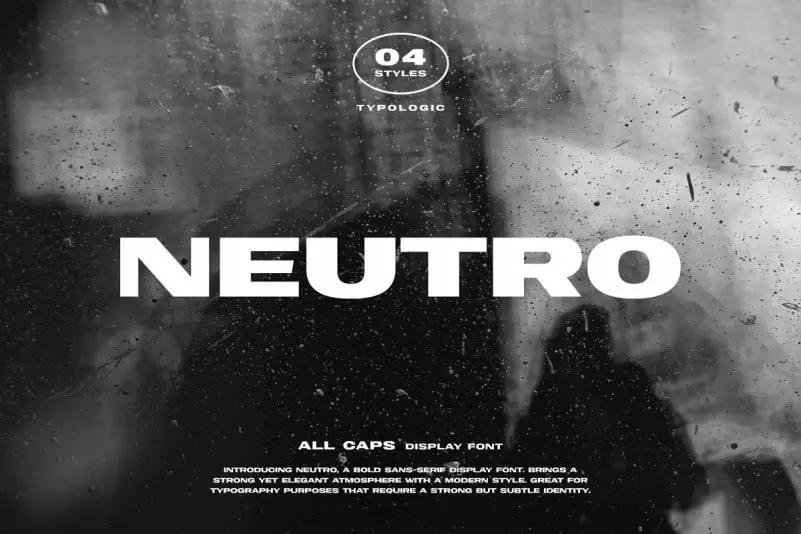
Neutro Display Font – Fonte Grátis
Neutro Display Font
Neutro Display Font é uma seleção poderosa e elegante de tipo para uso em aplicativos visuais, criada pela typologic com quatro pesos diferentes: regular, bold, extrabold e um versão em traços. Esta tipografia sans-serif foi projetada com um estilo moderno que traz atmosfera sofisticada e força sem ser ostensiva. É perfeita para aplicativos de design gráfico que precisam de uma identidade forte e discreta. Este tipo atende a uma ampla gama de necessidades, de materiais de marketing e publicidade até o design editorial ou ilustrações digitais, oferecendo um suporte visual elegante e moderno que tornará seus projetos ainda mais profissionais.